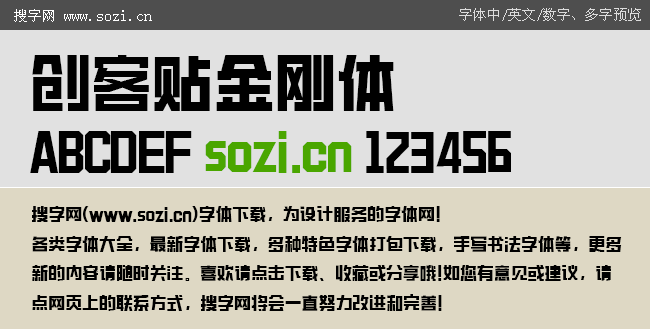
創(chuàng)客貼金剛體
搜字網(wǎng)給大家提供一款創(chuàng)客貼金剛體中文字體下載,創(chuàng)客貼金剛體是為支援抗擊疫情而創(chuàng)作的字體,字體寬實粗壯,簡潔有力。比較醒目,效果非常不錯。免費供大家使用。適合應(yīng)用于藝術(shù)設(shè)計、平面宣傳設(shè)計、網(wǎng)頁設(shè)計、海報設(shè)計等應(yīng)用。